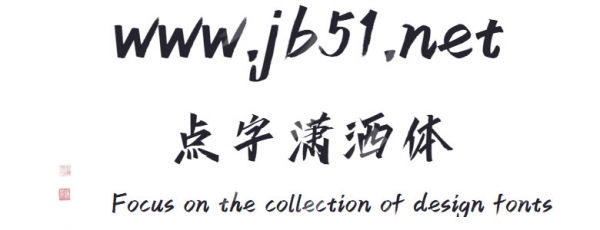
點(diǎn)字瀟灑體是由點(diǎn)字庫推出的藝術(shù)字體,字體字形瀟灑凌厲、剛勁有力,適合應(yīng)用于藝術(shù)設(shè)計(jì)、各類廣告和產(chǎn)品包裝設(shè)計(jì)等領(lǐng)域。
采用秀麗筆書寫。是一款創(chuàng)意書寫字體。整體字形瀟灑凌厲、剛勁有力。體現(xiàn)出字體年輕潮流的感覺。